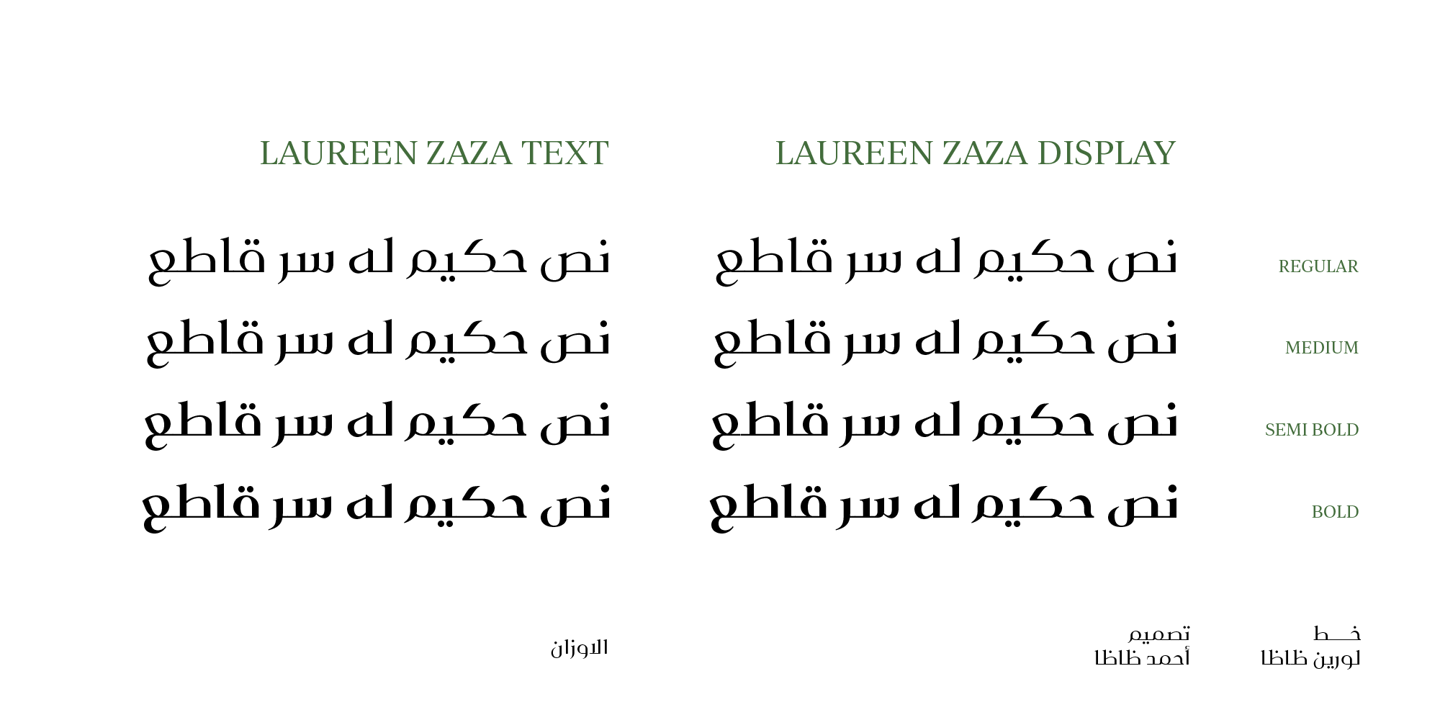
Laureen Zaza Font Family
Description de Laureen Zaza Font Family
Laureen Zaza est une police arabe qui possède un aspect très particulier. Il combine les caractéristiques de différents genres ; notamment le contraste des visages serif. Tandis que son design est influencé par le coufique et le style Naskh. Laureen Zaza se compose de deux polices de caractères, texte et affichage, et de 4 graisses. C’est un choix parfait pour les titres audacieux, la typographie surdimensionnée, les logos de mode, l’image de marque, l’identité, la conception de sites Web, les pochettes d’album, les couvertures, les affiches, la publicité, etc.